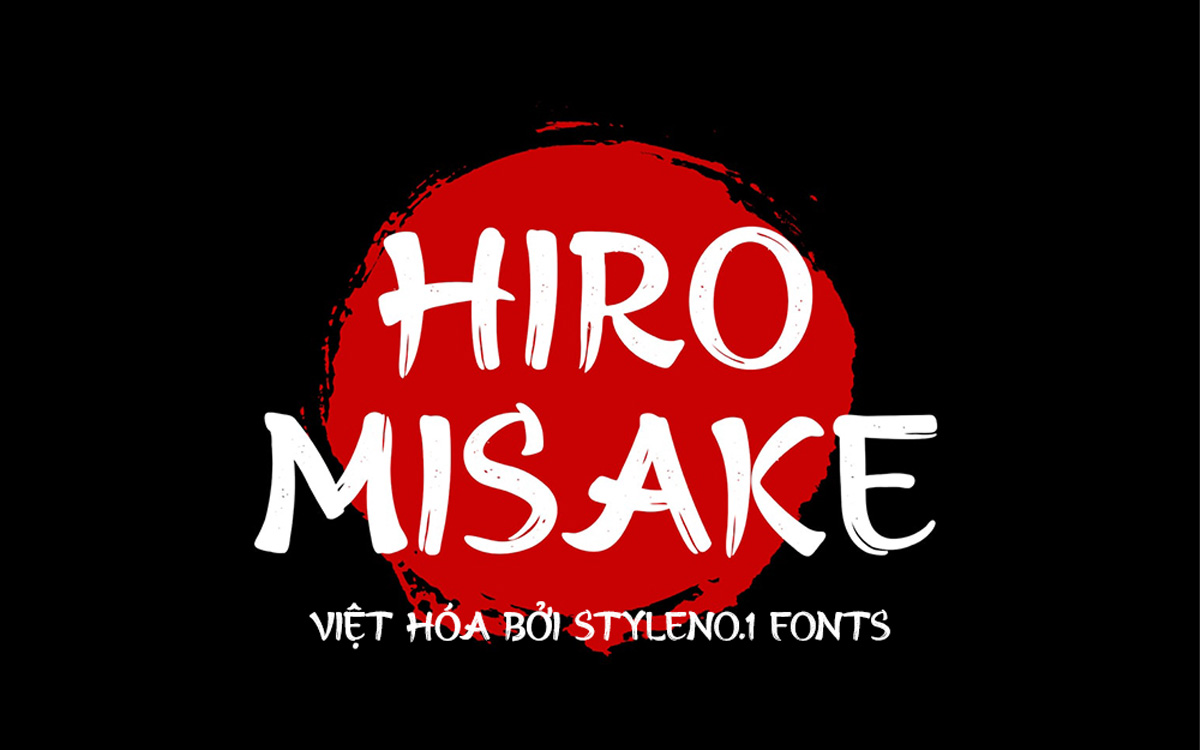
Font chữ brush Tokyo SVN-Hiro Misake
Font chữ brush Tokyo SVN-Hiro Misake là sự kết hợp hoàn mỹ giữa nghệ thuật thư pháp truyền thống Á Đông và tinh thần đường phố hiện đại đầy phóng khoáng của xứ sở hoa anh đào. Được Việt hóa tỉ mỉ bởi đội ngũ SVN, bộ font này mang đến những nét cọ thô mộc, dứt khoát và sắc sảo, giúp mọi ấn phẩm sáng tạo trở nên nổi bật và đậm chiều sâu cảm xúc. Đây chắc chắn là lựa chọn không thể bỏ qua đối với các nhà thiết kế đang tìm kiếm giải pháp typography mạnh mẽ, khác biệt cho dự án của mình.
Khám phá Font chữ brush Tokyo SVN-Hiro Misake – Biểu tượng nghệ thuật thư pháp đường phố ấn tượng
Trong thế giới thiết kế đồ họa đương đại, phong cách typography mang âm hưởng Nhật Bản luôn chiếm giữ một vị thế đặc biệt nhờ tính thẩm mỹ độc đáo, cân bằng giữa vẻ đẹp cổ điển và hơi thở tương lai. Font chữ brush Tokyo SVN-Hiro Misake ra đời như một sự tôn vinh văn hóa cọ vẽ truyền thống Sumi-e kết hợp nhịp sống ngầm (underground) sôi động của các con phố Shibuya, Shinjuku.
Điểm nhấn đặc biệt của bộ font này nằm ở cấu trúc chữ dạng cọ khô (dry brush) với đường nét xước tự nhiên, truyền tải trọn vẹn năng lượng thị giác mạnh mẽ và tốc độ của từng vệt mực. Phiên bản SVN-Hiro Misake đã được tinh chỉnh toàn diện về bảng mã tiếng Việt, mang lại sự thuận tiện tối đa cho cộng đồng sáng tạo tại Việt Nam mà không làm mất đi cái “hồn” nguyên bản của tác phẩm.
1. Nét cọ Dry Brush chân thực mô phỏng nghệ thuật thư pháp thủ công
Một trong những đặc tính đắt giá nhất của SVN-Hiro Misake chính là kết cấu bề mặt chữ vô cùng sống động. Từng ký tự không phải là những đường vector trơn láng đơn điệu, mà được vẽ thủ công với độ tưa rách, đậm nhạt ngẫu hứng giống như việc người nghệ sĩ dùng bút lông quét mực thô ráp trên nền giấy dó. Các chi tiết xước tự nhiên được giữ lại tinh xảo, giúp dòng chữ thể hiện được tính chuyển động và sức nặng thị giác vượt trội mà hiếm có font chữ số hóa nào làm được.
2. Hệ thống ký tự Việt hóa hoàn chỉnh và chuẩn ngữ pháp
Nhiều bộ font brush quốc tế khi nhập văn bản tiếng Việt thường gặp tình trạng lỗi dấu, dấu thanh quá nhỏ hoặc vị trí đặt dấu bị lệch lạc làm mất thẩm mỹ. Với phiên bản SVN-Hiro Misake, các ký tự có dấu như ă, â, đ, ê, ô, ơ, ư và các dấu thanh (sắc, huyền, hỏi, ngã, nặng) đều được thiết kế lại hoàn toàn thủ công. Tỷ lệ dấu được căn chỉnh hài hòa với tỷ lệ thân chữ, giữ nguyên độ nghiêng, lực nhấn và phong cách bụi bặm, đảm bảo bố cục chữ tiếng Việt luôn liền mạch và đẹp mắt.
3. Kho ký tự thay thế (Alternates) và Ligatures phong phú
Để tối ưu hóa tính độc bản cho từng tác phẩm, SVN-Hiro Misake tích hợp hệ thống OpenType Features đa dạng với nhiều glyphs thay thế và ký tự nối đôi. Các tính năng mở rộng này cho phép người dùng:
• Thay đổi các ký tự đầu dòng và cuối dòng với các nét vuốt (swashes) dài bay bổng, tạo điểm nhấn ấn tượng cho tiêu đề chính.
• Sử dụng các chữ cái thay thế (stylistic alternates) để tránh sự lặp lại đơn điệu khi hai ký tự giống nhau đứng cạnh nhau trong một từ.
• Khai thác các liên kết chữ (ligatures) mượt mà, giúp các cụm từ gắn kết tự nhiên như một tác phẩm viết tay thực thụ.
4. Khả năng ứng dụng linh hoạt trên đa dạng ấn phẩm truyền thông
Nhờ sở hữu phong cách vừa cổ điển, vừa hiện đại, SVN-Hiro Misake phù hợp với rất nhiều lĩnh vực và phong cách thiết kế khác nhau:
• Thiết kế Poster & Key Visual: Tạo nên những poster phim hành động, sự kiện âm nhạc điện tử, lễ hội văn hóa Á Đông hoặc giải đấu thể thao điện tử (Esports) đầy kịch tính.
• Thời trang Streetwear: In ấn trực tiếp lên áo thun, hoodie, áo khoác bomber hoặc phụ kiện mang phong cách hip-hop, techwear, anime/manga.
• Bao bì sản phẩm & Ẩm thực: Thiết kế bao bì trà đạo, rượu sake, menu nhà hàng Nhật Bản, ramen bar hay bao bì các mặt hàng thủ công mỹ nghệ.
• Nhận diện thương hiệu: Thích hợp làm logo hoặc slogan cho các thương hiệu võ thuật, phòng gym, studio xăm nghệ thuật (tattoo), gaming gear.
Bí quyết phối font (Font Pairing) đỉnh cao cùng SVN-Hiro Misake
Bởi vì SVN-Hiro Misake là một font chữ mang tính trình bày cao (Display Font) với cá tính cực kỳ nổi bật, bạn nên áp dụng các nguyên tắc phối font sau để tác phẩm đạt hiệu quả thẩm mỹ tốt nhất:
1. Kết hợp với font Sans-serif hình học: Đặt tiêu đề chính bằng SVN-Hiro Misake và sử dụng các font không chân tối giản, sạch sẽ như Montserrat, Roboto, Bebas Neue hoặc Helvetica cho phần phụ đề và văn bản nội dung. Sự tương phản giữa nét cọ thô ráp và đường nét thẳng tắp sẽ làm nổi bật tiêu đề chính.